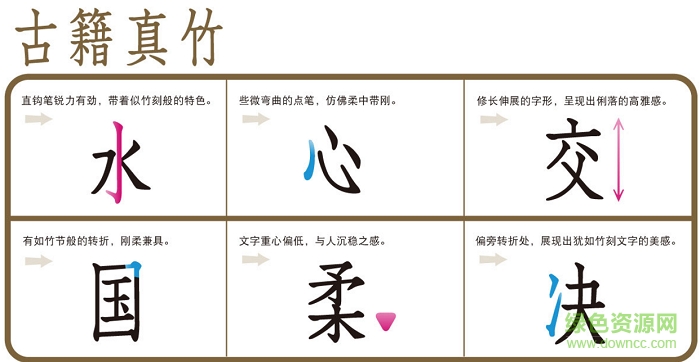
華康古籍真竹w3 p字體是一款清秀有力的華康字體,筆畫(huà)強(qiáng)勁又不失柔軟,姿態(tài)悠然,雅韻脫俗,十分好看,綠色資源網(wǎng)還有全套華康古籍字體等你下載,快來(lái)收藏吧!
以宋代文學(xué)家王安石(1021~1086)選輯的《唐百家詩(shī)選》為本,取該書(shū)中字形瘦長(zhǎng)秀氣的竹刻文字,其筆劃尖端似青翠真竹,故命名為「古籍真竹」。字體重心低,筆劃轉(zhuǎn)折處似竹節(jié)般強(qiáng)勁,又兼具柔韌筆觸,可窺得悠然自得的樣貌。適合內(nèi)文和直式書(shū)寫(xiě)。
古籍真竹適合內(nèi)文和直式書(shū)寫(xiě),似傳統(tǒng)版刻風(fēng)格,編排于書(shū)刊雜志中,流露出充滿古典韻味的氣息。也適合應(yīng)用于傳統(tǒng)技藝產(chǎn)品、食品之包裝。
古籍五書(shū)體中的古籍真竹,瘦長(zhǎng)挑高,筆直挺勁,猶如走入竹林的視覺(jué)意象。這套字體取材自坊間所復(fù)刻的宋代王安石 《唐百家詩(shī)選》,設(shè)計(jì)師偶然的機(jī)會(huì)下接觸此書(shū),在古詩(shī)的平仄韻律中,感受古代詩(shī)人詠人、詠物的情意;但身為字體設(shè)計(jì)師,總是在字意之外,更為字形所深深吸引。